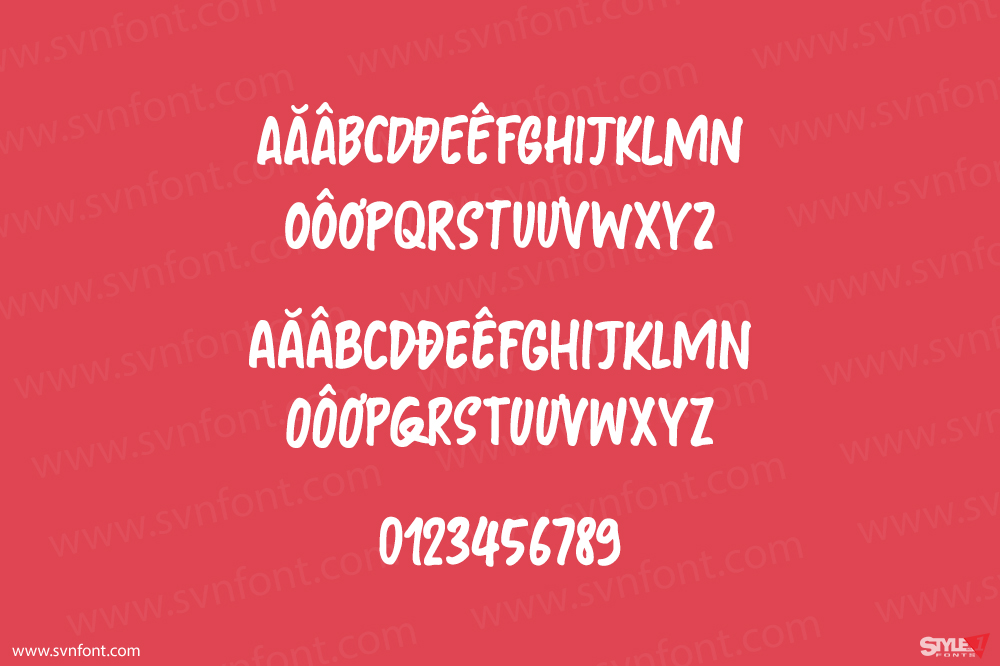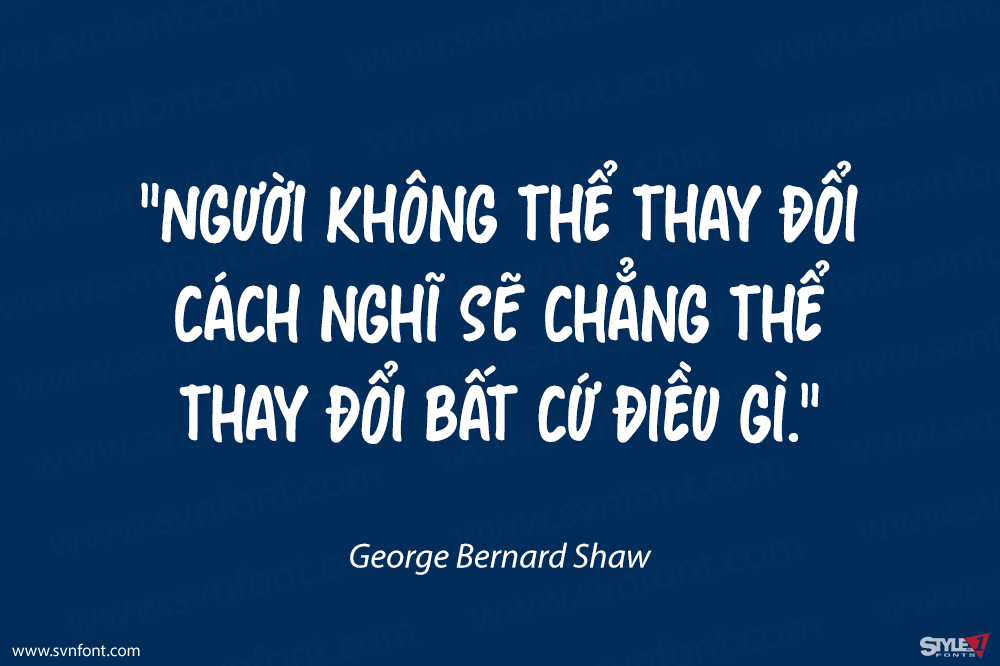
Shibby (tính từ, v.v.). Được dùng để chỉ một điều gì đó “ngầu”. Rõ ràng Shibby lần đầu tiên được sử dụng trong bộ phim “Dude, Where’s My Car?” năm 1999. Tôi không nghĩ Shibby là từ “ngầu” của thời điểm hiện tại, nhưng tôi nghĩ nó đủ ngầu cho phông chữ khá “shibby” này!